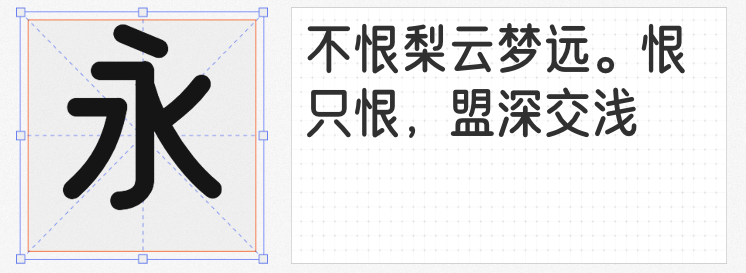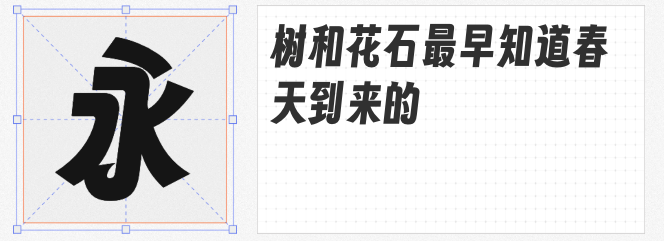
在商业设计领域,兼具亲和力与传播力的可爱风字体正成为品牌年轻化、IP形象塑造的利器。本文精选四款免费商用字体,从结构创意到细节打磨,解析其如何以独特设计语言传递治愈感与时尚感,助力设计师打造高辨识度视觉作品。
以“得意黑”为基底,字魂扁桃体通过加粗字重与加宽字身强化力量感,搭配标志性的喇叭口微笑弧度设计,让文字自带“上扬嘴角”的视觉联想。例如,在儿童教育品牌LOGO中,其圆润的笔画与向上卷曲的弧度,可快速传递快乐与亲和力;在零食包装标题中,夸张的喇叭口设计则能增强视觉冲击力,吸引年轻消费者目光。
采用窄长字形与厚底弧线的组合,Aa厚底黑在保持现代简约感的同时,通过底部加厚的视觉处理赋予文字“萌系”气质。其笔画转折处的圆润弧度与纵向拉伸的字体结构,使文字在屏显场景中更具轻盈感。例如,在咖啡品牌海报中,其厚底设计可模拟杯底倒影的趣味效果;在社交媒体表情包设计中,窄长字形则适配竖版排版,强化动态感。
以纵向拉长的圆体结构为核心,优设鲨鱼菲特健康体在保留圆润弧度的基础上,通过硬挺笔划转角与纤细中宫的平衡,塑造出兼具健康感与时尚感的视觉风格。例如,在运动品牌宣传中,其纵向延伸的笔画可隐喻体态的修长与活力;在轻食包装设计中,硬挺的转角细节则提升品质感,避免圆体字体的稚嫩感。
基于日文字体ステッキ / Stick改编,游趣体以直线笔杆造型与田园写意风格为特色,通过OpenType特性优化中文排版适配性。其笔划末端的钝化处理与适度的倾斜角度,赋予文字“手写涂鸦”般的自然感。例如,在文创产品包装中,其直线设计可模拟铅笔书写效果;在儿童绘本插画中,田园风格则与自然主题场景完美融合。
设计师可根据品牌调性,灵活运用字体特性,在商业设计中实现情感共鸣与视觉美学的双重突破。